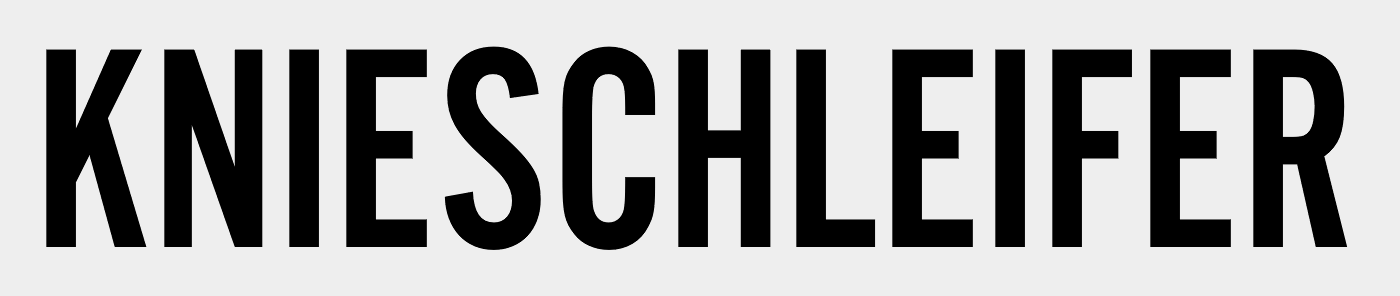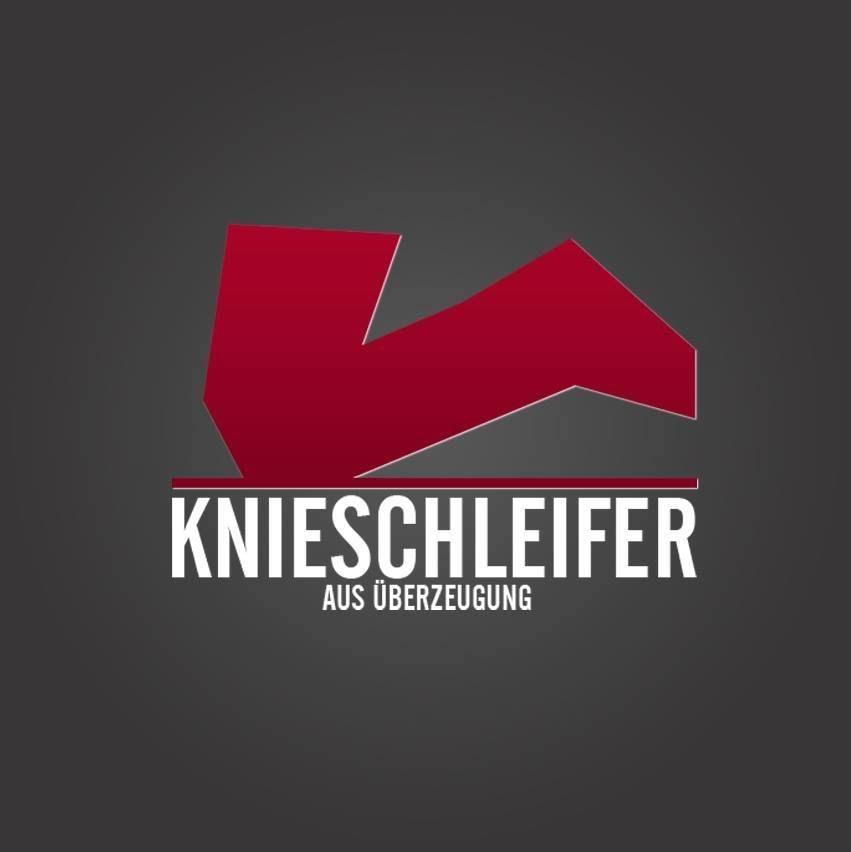
Wie heißt die Schrift die die "Knieschleifer" verwenden?
ein Freund hat mich gefragt ob ich ihm ein Logo für seine neu Gegründete Knieschleifergruppe mache, daher suche ich die Schrift die die "Knieschleifer" in ihrem logo verwenden.
Die hier genannten Selbst-Erkennungs-Tipps schon probiert?
WhatTheFont sagt Alternate Gothic Nr 2
Vielleicht müssen wir hier ja mal ein Tutorial bauen: Wie bereite ich eine Schriftdarstellung für die Suche mit WhatTheFont, WhatFontIs und Font-Matcherator auf.
Bis aufs R stimmt die Alternate Gothic No2. Das R wurde entweder angepasst (unterer Querstrich ist original niedriger als mittlerer Querstrich beim E oder F) oder es ist eine andere Schrift.
Letztlich unterschieden sich die beiden nur in Details, hier eine andere Rundung, dort ein µ breiter oder schmäler. Die Trade Gothic Condensed auf 88 % Breite ist dann annähernd deckungsgleich mit der Alternate Gothic.
Die gezeigte Alternate Gothic ist nur ein Klon der Trade Gothic Bold Condensed No. 20, oder?
Wobei Morris Fuller Bentons Alternate Gothic ja an sich einige Jahrzehnte vor der Trade Gothic gestaltet worden ist.